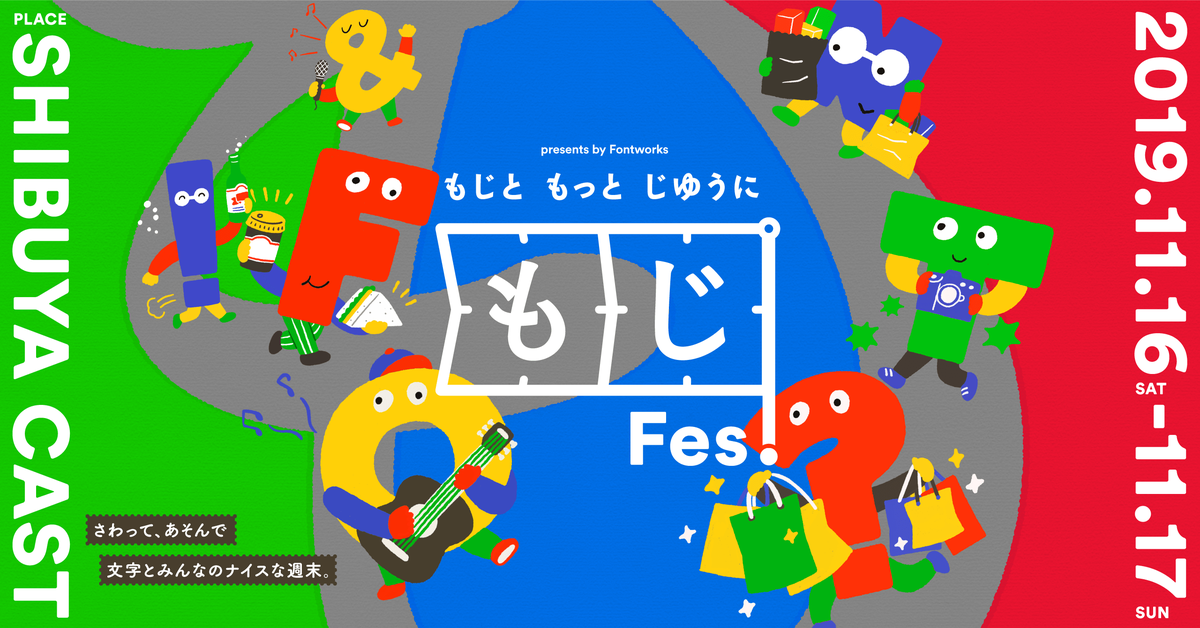
もじFes.
2019年11月16日(土)・17日(日)にフォントワークスは「渋谷の街で、さわって、あそぶ」文字のフェスティバル「もじFes.」を、クリエイティブ・エージェンシーのCampと共に渋谷キャストで開催することを発表した。
「もじFes.」は、日常に潜むたくさんの「文字」を、モノや音楽、食など「文字と◯◯」をテーマに様々なな入り口から体験する、大人から子どもまでみんなに開かれたフェスティバル。展示・ワークショップ・ライブ・トークセッション・フード&ドリンク・AR体験など、文字とデザインの楽しい世界をからだいっぱいに味わう、刺激的なプログラムが用意されている。
「もじFes.」の全プログラムが決定!約20組参加のマーケット、カラテカ矢部太郎(※闇営業ではない、多分…)など豪華アーティストによる朗読会や日本唯一のSnapchat公認クリエイターによるARプログラムなどが実施予定!!
2019年11月16日(土)・17日(日)にCamp Inc.が、筑紫書体やロダンなど多くの人に愛されるフォントを企画・開発し創業25周年を迎えたフォントワークス株式会社と共催する、文字のフェスティバル「もじFes.」の全プログラムと、イベント企画に漫画「大家さんと僕」にて第22回手塚治虫文化賞短編賞を受賞した、お笑い芸人の矢部太郎(カラテカ)氏、シンガー・ソングライターで文筆家の寺尾紗穂氏の出演が決定した。
「もじFes.」は、渋谷キャストの屋内外で開催される、私たちの日常に潜むたくさんの「文字」を、モノや音楽、食など「文字と◯◯」をテーマにさまざまな入り口から体験する、大人から子どもまでみんなに開かれたフェスティバル。文字と出会い、遊び、味わいながら学べる、文字とデザインの世界をからだいっぱいに味わえる全11のプログラムが実施される。
「フォント・マーケット」には、『WIRED』日本版のコミックなどを手掛ける北村みなみ氏と、多くの交通機関や施設のサインに採用されている「たづがねR」デザイナー山田和寛氏によるユニット「謝謝社」をはじめ、約20組のクリエイターが参加予定。
屋外エリアの「渋谷キャスト ガーデン」では、文字をテーマにこの日のためにつくられたアクセサリーやイラスト、クラフト作品などが並んだり、美しい文字や面白い文字、もじFes.オリジナルキャラクターをシールにした限定インスタントタトゥーの無償配布や、似顔絵ブースが連なる【フォント・マーケット】、代官山など全国4ヶ所で人気の「SPRING VALLEY BREWERY」のクラフトビールや、表参道でクリエイターに愛される「forucafe」のドリンクの無償引換券にもなる活版印刷のコースターづくりワークショップ【活版TOKYO in もじFes.】、ビッグサイズの「SHIBUYA」の文字を裏から見たり中から覗いたり、文字の構造を体感できる【巨大文字のインスタレーション】を開催となる。
▼屋内エリアでは、入ってすぐに大きな文字のインスタレーションが現れる
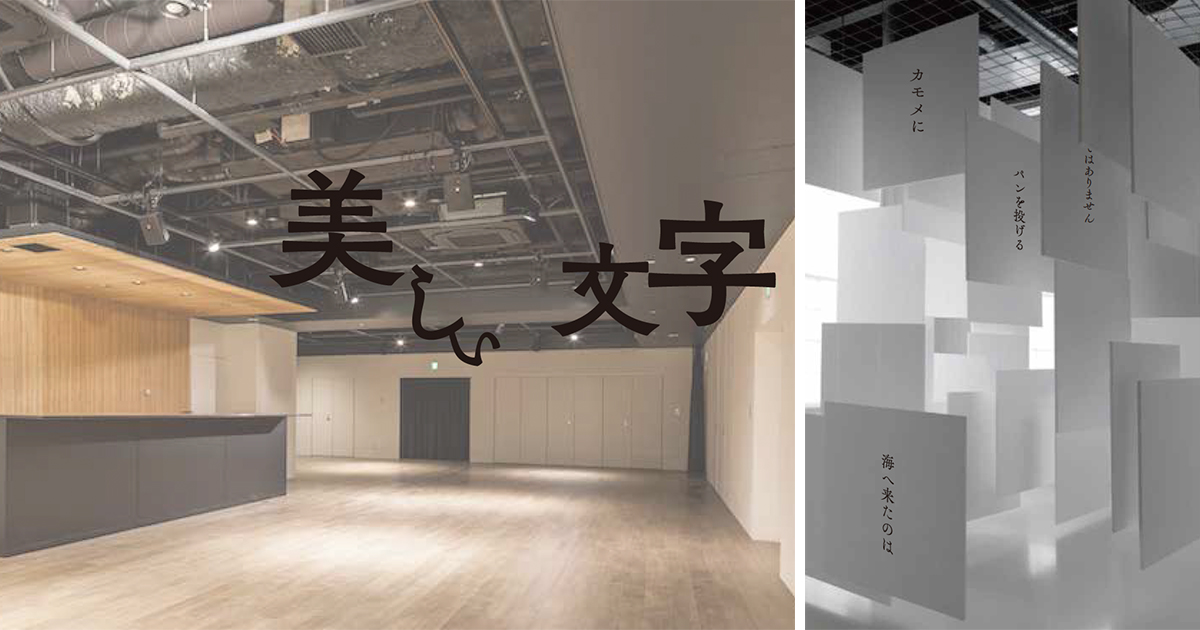
屋内エリアの「渋谷キャスト スペース」では、文字の雰囲気と物語の内容のギャップを、お笑い芸人・漫画家の矢部太郎(カラテカ)氏、シンガー・ソングライターで文筆家の寺尾紗穂氏ら豪華アーティストによる朗読で楽しむ【ギャップ朗読会】、ひとつの漢字で異なるフォントのパーツ(部首)を組み合わせて遊びながら書体を学べる【“愛”の見本帖】、フォントデザイナーやクリエイターがオススメする文字の表現が秀逸な本を紹介する選書展【文字好きが選ぶ、文字の本】、映画『翔んで埼玉』の美術協力や美文字レッスンで人気の書道家・目時白珠氏と一緒に、“古代の絵文字”といえる甲骨文字を書くワークショップ【甲骨文字を書いてみよう!】、古い町並みにたたずむ個性的で味のある文字を「のらもじ」と名付け「発見→分析→フォント化」する「のらもじ発見プロジェクト」によるワークショップ【のらもじTシャツづくり】【のらもじレタリング缶バッジづくり】といったラインアップで盛りだくさんのプログラムを開催となる。
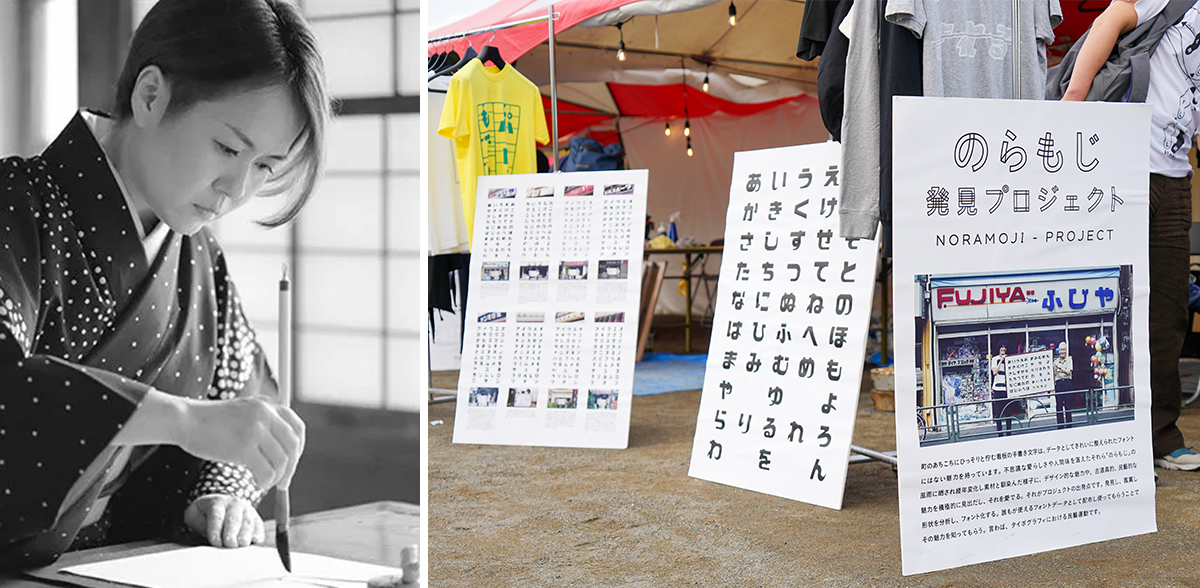
また、フード&ドリンクスタンドでは、Brooklyn BreweryのもじFes.限定オリジナルグッズ付クラフトビール、味によって異なるコースターでオーダーするSPRING VALLEY BREWERYのクラフトビール、forucafeによる日本初のブリュレフレンチトーストといったスイーツやほっと温まるスープなど、秋にぴったりの文字を味わうメニューが提供される。
「文字」をコンセプトに、秋の旬の味わいを楽しめるフードやアルコール、ソフトドリンクを提供。
そして今回、日本で唯一のSnapchat公認クリエイター青絵氏による、【フォントワークスオリジナルARフィルター】が公開された。
スマホアプリ「Snapchat」でフォントワークスオリジナルのARフィルターへアクセスすると、「もじFes.」オリジナルキャラクター「エフくん」がARで出現。カメラをかざすと、跳びはねたり大きさが変わったりする変幻自在なキャラクターと、文字の世界をさらに楽しめる。(スナップチャットおよび「エフくん」のARフィルターは無料。)
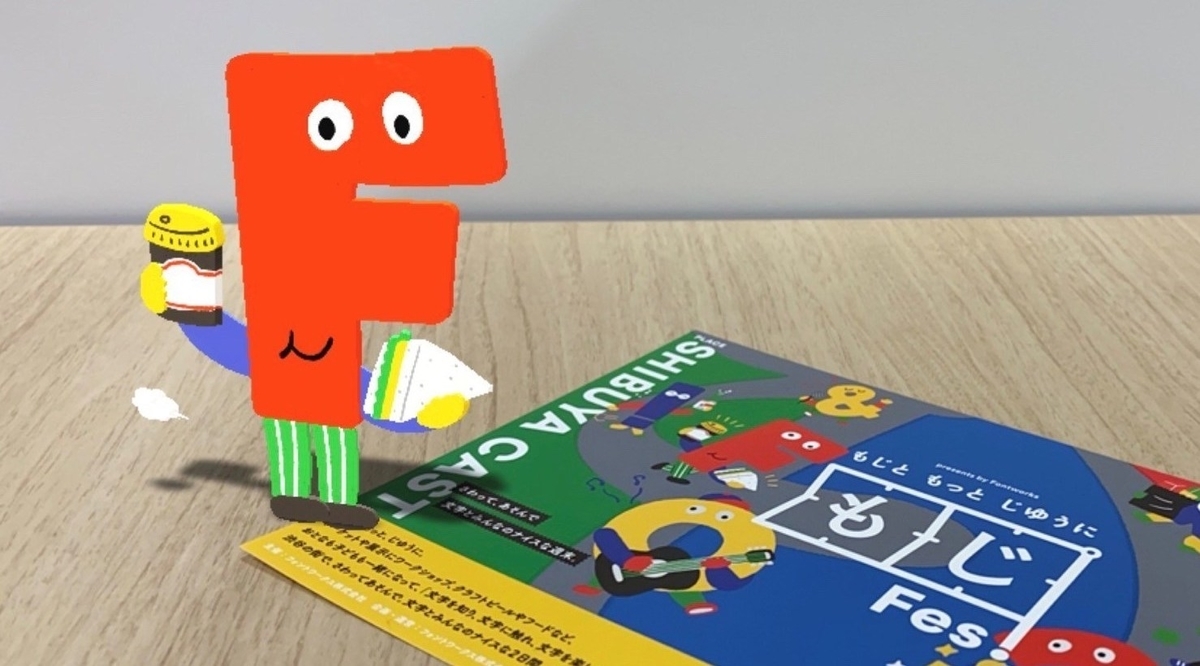
プログラム【屋外エリア】
●「フォント・マーケット」
「文字」をテーマにこの日のためにつくられた作品や、特殊製法でつくられたインスタントタトゥーの無償配布、活版印刷のワークショップなどを開催。
《マーケットブース参加作家》
YAMADA ZOMBIE/SUEKKO LIONS/謝謝社/松岡マサタカ/イシバシアキ/松本康孝/TSUDA KYOKO/山上淑惠/Dig-a-doo/橋本太郎/instanttattoo/Hako de kit/Aui-AO Design/活版TOKYO(中野商店)/Print Works Shibuya/PRIMART
《似顔絵ブース参加作家》
かこまき/さめほし/水元さきの(17日のみ)
●「活版TOKYO in もじFes.」
活版印刷を体験できるワークショップ。味わいによって異なる文字でデザインされたコースターは、屋内のドリンクスタンドの一部クラフトビールの引換券に。
コースターづくりワークショップ@フォントマーケット内
筑紫書体の見本帖づくりワークショップ@大階段下
※いずれも2日間終日開催
●「巨大文字インスタレーション」
文字の構造を体感できる、大人も子どもも楽しいフォトジェニックな巨大文字。
※雨天の際は屋内にて実施いたします
プログラム【屋内エリア】
●「“愛”の見本帖」
異なるフォントの「愛」のパーツ(部首)を組み合わせ、見比べたり写真を撮ったり、遊びながら書体を学べる参加型プログラム。
●「もじ好きが選ぶ、もじの本」
文字やデザインのプロフェッショナルが選ぶ、「これぞ!」というデザインや文字組みの本を公開。国内外、単行本や絵本やZINEなど、さまざまな「もじ本」が楽しめる。
《イベント・ワークショップ》
●「ギャップ朗読会」
映し出される文字の雰囲気と物語の内容のギャップを、漫画「大家さんと僕」の作者であり、お笑い芸人の矢部太郎(カラテカ)氏、シンガー・ソングライターで文筆家の寺尾紗穂さん氏をはじめ豪華アーティストらによる朗読で味わうスペシャルプログラム。
2日間連続開催
※日によって朗読者が異なる。順次公式Webサイトにて公開。
[出演者]
矢部太郎(カラテカ)
1977年生まれ。お笑い芸人としてだけでなく、舞台やドラマ、映画で俳優としても活躍している。
初めて描いた漫画作品『大家さんと僕』で第22回手塚治虫文化賞短編賞を受賞、同書は80万部超の大ヒットに。父親は絵本作家のやべみつのり。
寺尾紗穂
2007年ピアノ弾き語りアルバム「御身」をリリース。2010年よりビッグイシューを応援するイベント「りんりんふぇす」を主催。大林宣彦監督の「転校生 さよならあなた」、安藤桃子監督の「0.5ミリ」などの主題歌やCM(ドコモ、三井のリハウス他)製作や著書や連載も多数。最新アルバムは「君は私の友達」。あだち麗三郎、伊賀航と組んだ「冬にわかれて」でも活動中。
●「甲骨文字を書いてみよう! by 目時白珠」
「古代の絵文字」ともいえる甲骨文字を、書家と一緒に書くワークショップ。
2日間連続開催 ※内容は同じ。
●「オリジナルTシャツづくり」「レタリング缶バッジづくり」ワークショップ by のらもじ」
シルクスクリーンでレトロなデザインのTシャツを手刷りする「オリジナルTシャツづくり」、街で発見した文字を題材に、好きな言葉をレタリングして缶バッジにする「レタリング缶バッジづくり」といった、レトロな文字たちと遊べる2つのワークショップを、のらもじ発見プロジェクトが開催。
※レタリング=文字をデザインしたり、デザインされた文字を書くこと
※日によって内容が異なる。
11月16日(土)「オリジナルTシャツづくりワークショップ」
11月17日(日)「レタリング缶バッジづくりワークショップ」
「文字」を意識すると、私たちの表現力はもっとひろがる「もじFes.」